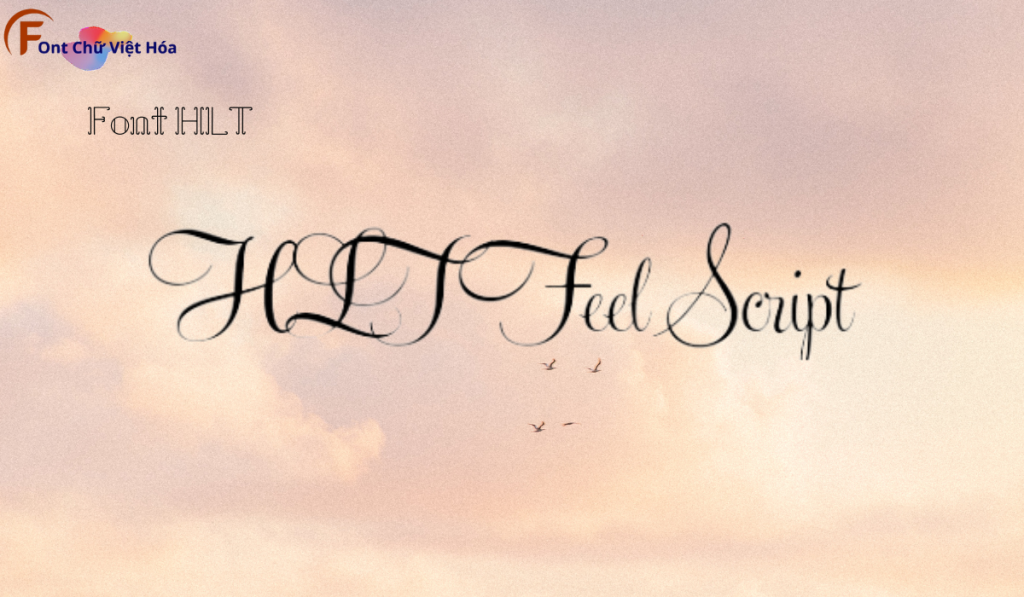
Font HLT Feel Script Việt Hóa
Tác giả: HLT Feel Script
Bộ Font: HLT
Kiểu chữ: Chữ viết tay
Font HLT Feel Script Việt Hóa là một font chữ viết tay cá tính, thuộc bộ font HLT. Được thiết kế với mục tiêu mang lại sự mềm mại và thanh thoát, font này lý tưởng cho các dự án thiết kế như thiệp mời, logo, và bao bì sản phẩm. Với các nét chữ uyển chuyển và độ dày đều đặn, Font HLT Feel Script Việt Hóa không chỉ dễ đọc mà còn tạo cảm giác thân thiện và gần gũi.